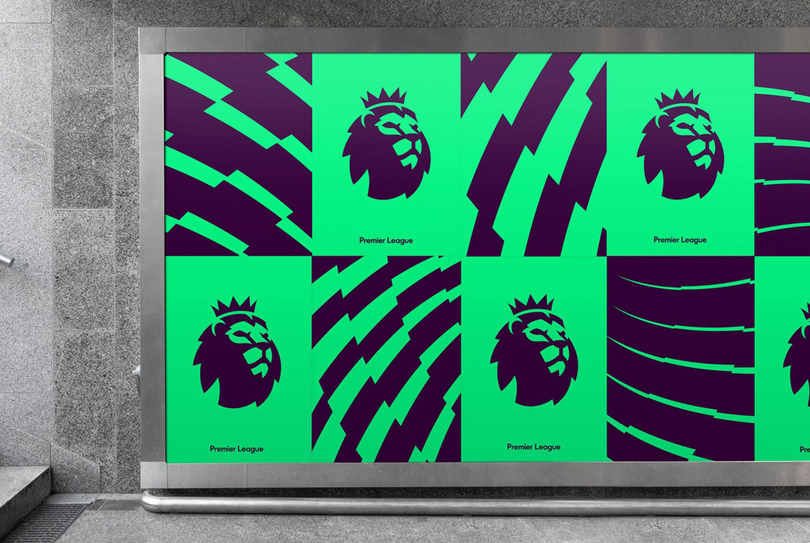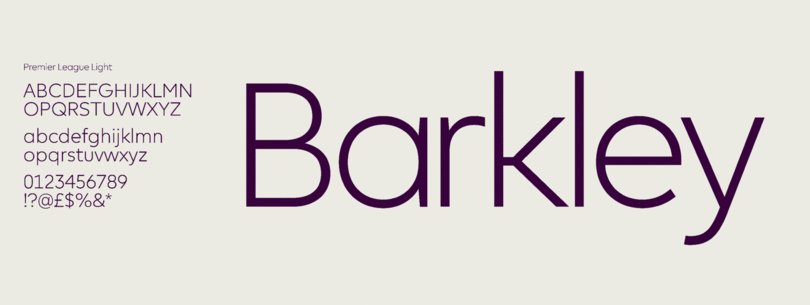
Premier League : Une identité de marque qui travaille dur, joue dur.
Toshi Omagari, designer typographique chez Monotype, a travaillé en étroite collaboration avec le DesignStudio pour créer pour Premier League une police sans serif géométrique très performante, qui puisse s’afficher avec assurance sur un grand nombre de supports – écrans, maillots, télévision et tableaux de classement.
Auparavant, Premier League utilisait une police de caractères tout en capitales. Elle cherchait donc à adopter un ton de voix plus frais et conversationnel, ainsi qu’un design capable de s’adapter aux exigences de différents médiums. La concurrence entre les ligues européennes de football professionnel n’ayant jamais été aussi forte, cela devait aider la marque à se démarquer visuellement et commercialement.
Logo de Premier League, avant et après.
Nous nous éloignons de quelque chose qui avait été conçu il y a dix ans et qui n’était pas adapté pour l’ère numérique », déclare l’équipe de DesignStudio. « Quand nous avons redessiné le lion, tout semblait plus net et plus simple. Nous avions besoin d’une typographie qui ait un impact à grande échelle, tout en étant apte à fonctionner sur les applications numériques.
La police de caractères devait pouvoir fonctionner lorsqu’elle était en grande taille, mais aussi à une échelle beaucoup plus petite, lorsqu’elle était utilisée dans des tableaux et des styles condensés – notamment pour les noms de joueurs particulièrement longs. Cela a nécessité quelques expériences typographiques inhabituelles. Le nom du joueur anglais Alex Oxlade-Chamberlain a été choisi comme scénario de test d’utilisation.
«C’est l’un de ces cas où l’on se rend compte que le fait d’avoir une police massive tout en majuscules ne fonctionnera pas », explique DesignStudio. « Travailler autour de cela était amusant.»
C’est dans un mot-symbole dessiné pour la première fois par DesignStudio au début du rebranding, que la police trouve son origine. Reprenant les hampes légèrement effilées des minuscules r, g et m, Omagari a travaillé en étroite collaboration avec le studio pour traduire ces détails dans l’ADN pour une famille complète. Le designer a passé du temps dans les bureaux du studio à l’est de Londres, travaillant avec l’équipe pour dessiner des lettres imprimées en d’énormes tailles, et travaillant sur des ajustements au fur et à mesure des suggestions du studio.
«Nous savions que la police serait beaucoup utilisée à la télévision et sur support mobile, il était donc essentiel que les chiffres soient différents et distincts», explique Omagari.
Bien que Premier Sans doive performer et franchir tous les points de contact – télévision, diffusion, impression, site Web, applications et tout ce qui se trouve sur le terrain – il était également essentiel qu’elle transmette une nouvelle personnalité pour la marque, sans avoir peur de montrer son caractère.
«Fondamentalement, c’est une police de caractères fonctionnelle, mais à partir de là, c’est possible d’insuffler une touche festive», ajoute le studio.
«Nous avons travaillé avec Toshi pour trouver des caractères qui pourraient être plus intéressants, et nous sommes ensuite passés aux chiffres et à la ponctuation. Il s’agissait de rechercher des éléments qui ne reflétaient pas la façon dont le texte était lu en tant que bloc de texte, mais qui ajoutaient de la personnalité aux textes agrandis et aux titres.»
De très légers angles ajoutés au sommet des verticales ont permis de distinguer la police des autres sans serifs géométriques. Les chiffres, en particulier, sont devenus un point de mire, car ils nécessitent d’être facilement reconnus sur les horloges, les tableaux et pour d’autres utilisations à l’écran.
«Nous savions que la police serait beaucoup utilisée à la télévision et sur support mobile, il était donc essentiel que les chiffres soient différents et distincts», explique Omagari.
Il était également essentiel que la police aide Premier League à s’aligner visuellement avec un tout nouveau monde de l’image de marque – non seulement les autres organisations sportives, mais aussi les entreprises comme Google, Apple et d’autres menant la charge.
«Nous cherchions quelque chose de beaucoup plus personnel et ouvert », ajoute DesignStudio. « Qui puisse être un contemporain du monde de ces marques.»
«Quand les gens regardent le football maintenant, ce qui les distrait se trouve sur leur téléphone et leur ordinateur. C’est contre ces éléments que nous rivalisons, autant que contre les autres marques de sport.»